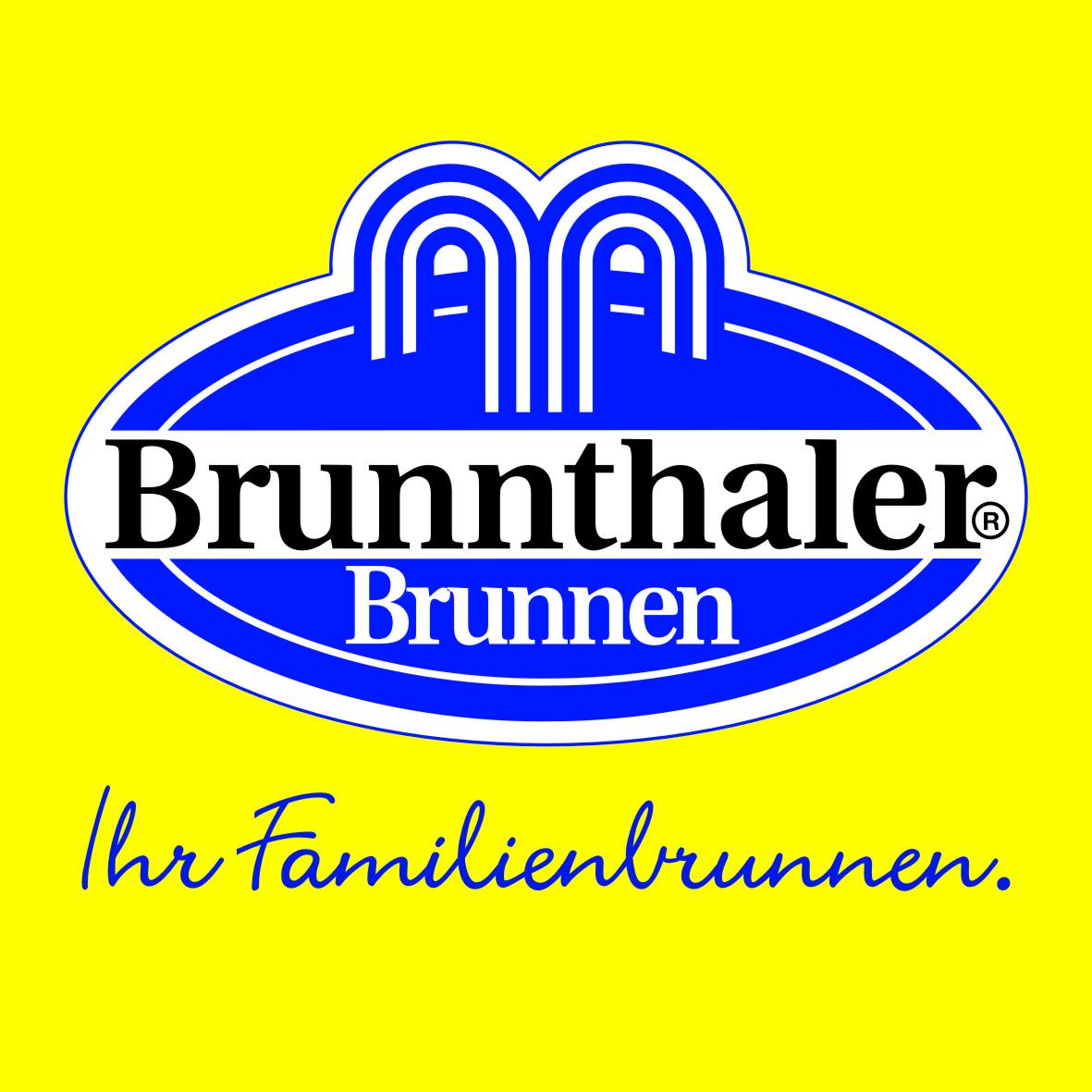
Suche Schriftart vom Logo des Getränkeherstellers Brunnenthaler
kennt jemand die Schriftart von "Ihr Familienbrunnen"?
Der Schriftzug ist Bestandteil des Logos von Brunnthaler, ein Getränkehersteller aus dem bayerischen Ort Burgheim.
Das F hab ich doch auch schon gefühlt tausendmal gesehen, ich komm aber nicht drauf … :-(
Ist das überhaupt nur 1 Schrift? Das I und F sehen mir so aus, als würde sie durch die unterschiedlichen Dicken nicht zu den Kleinbuchstaben passen.
Danke euch beiden! Also für die Kleinbuchstaben nehme ich die Bickley Script und mache es fetter. Die beiden Großbuchstaben sind wohl eine andere Schriftart, die werde ich nachzeichnen.